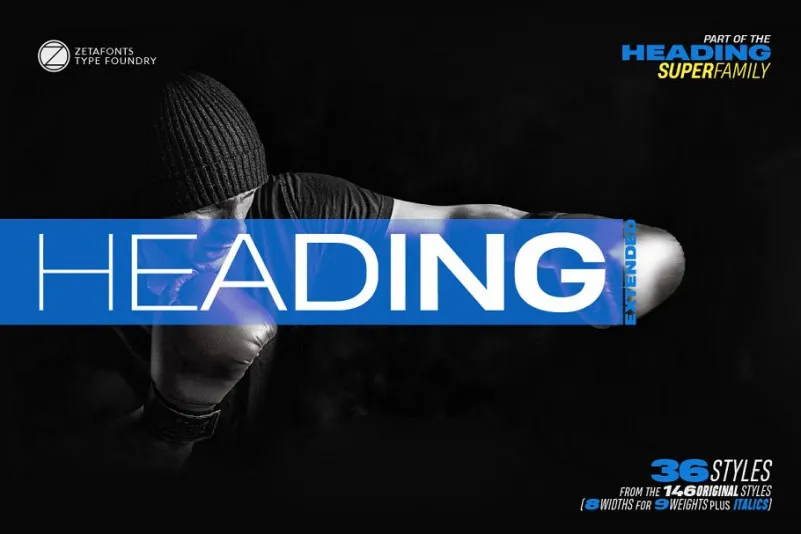
Heading Pro Wide Font Family
Introduzimos Heading Pro Wide Font Family, uma família tipográfica extensa criada pelo designer italiano Francesco Canovaro para a Zetafonts. Este é um tipo aberto de sans-serif redondo baseado em formas geométricas. É perfeitamente adequado para quase qualquer aplicação de design criativo. Com esta nova versão wides, temos agora duas famílias de largura ampliada que foram adicionadas à família original de comprimento reduzido, otimizando o uso para títulos onde a estilo e energia puro são mais importantes do que economia de pixels ou papel. Mantendo fiel ao design original de Heading, com uma atenção (post) modernista à leitura e detalhes, as grandes proporções permitem escrever headlines poderosas e jogos interessantes com sub-títulos e blocos de texto curtos. As itálicas compatíveis fornecem versatilidade na utilização do texto, bem como alternativas de exibição viáveis para pesos mais grossos, com um forte senso de esportes e energia. Cada tipoface Heading Pro inclui mais de 800 caracteres, cobrindo centenas de línguas que usam o alfabeto latino, cirílico e grego. Uma ampla gama de recursos do tipo aberto está inclusa em cada peso, como alternâncias estilizadas, minúsculas grandes, numerais de estilo antigo e números tabulares, além de figuras posicionais.